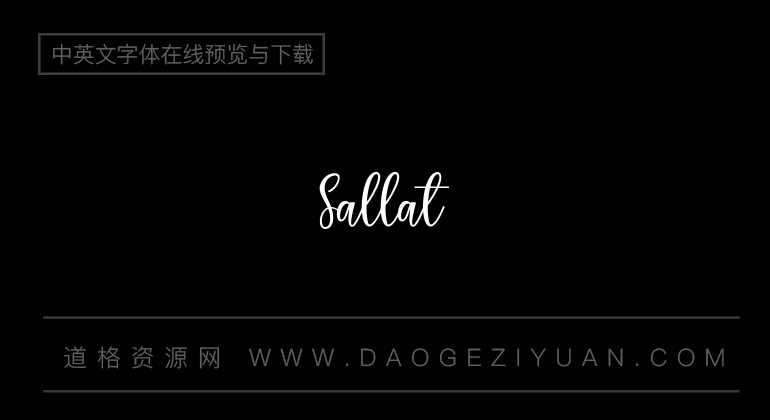
Sallat
? Sallat 是一款由比利时设计师 Sander De Winne 创作的简洁、优雅的字体。它具有清晰的轮廓线条,细节丰富,给人一种极致的视觉感受。它的字形设计极具语义,可以帮助提升文字的可读性,让文字更加醒目、生动。Sallat 字体可以用于各种不同的设计项目,如广告、海报、书籍、网站、包装等,也可以用于印刷品的设计,是一款非常适用的字体。
Sallat是一款非常不错的手写艺术字体,具有很好的视觉感,适合于文化类的宣传设计、商业类品牌的广告和产品包装设计以及个性化文字排版等较多场景。